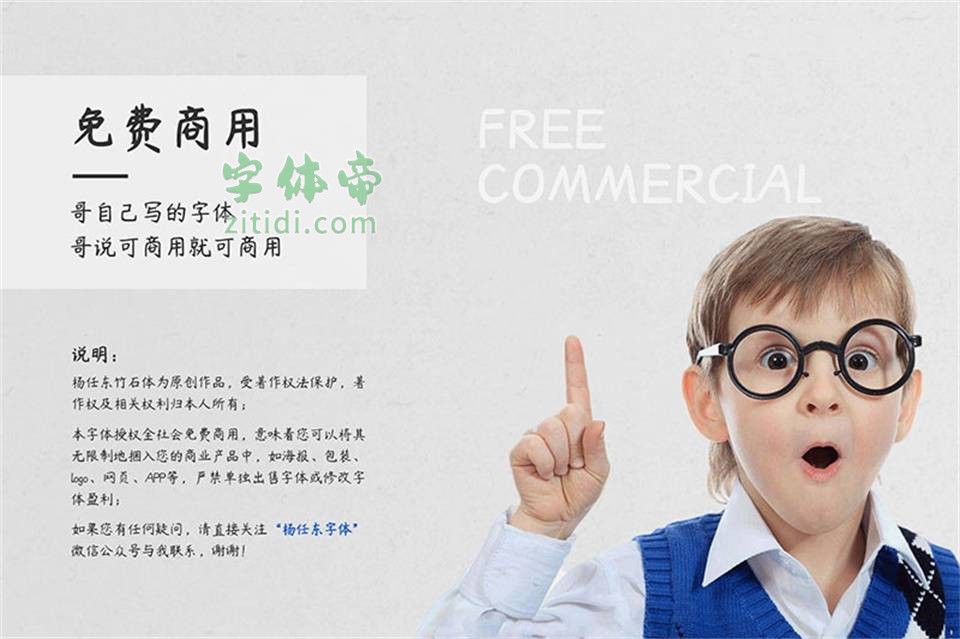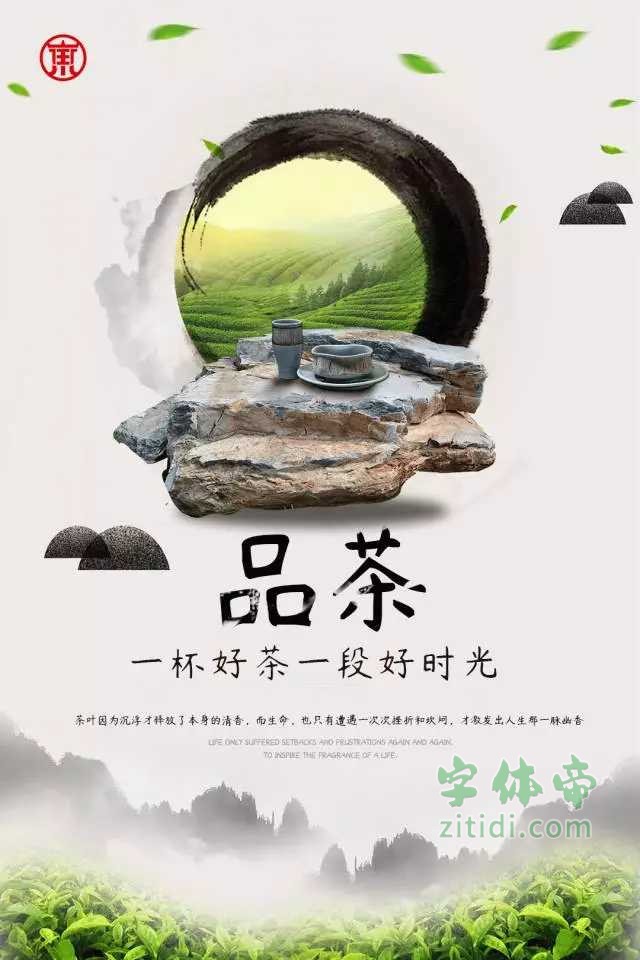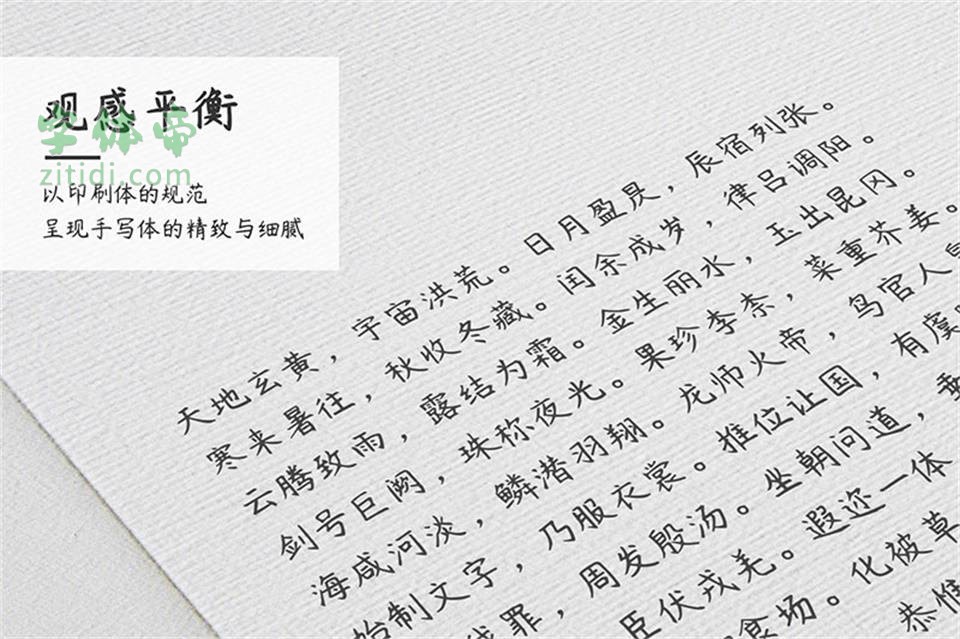
拿字体版权问题来说,形势可谓十分严峻。高额的字体授权费用和许多版权归属不明朗的字体始终困扰着设计师。而现实情况是免费可商用的字体少之又少,字体盗版情况屡禁不止。那么字体还能不能好好用了?答案当然是:能!全球首款七字重中文手写字体,杨任东竹石体正式发布!重点是,免费可商用!!!
杨任东竹石体按照GB2312-80书写,并增补了少量常见汉字,单个ttf格式字体文件包括7311个字符,涵盖了日常生活用字99.8%的需求;整套字体有7个字重,也就是共有7个ttf格式字体文件,全套字体共计50000余个字符。
本套字体的部分文字还存在重心不一致、细节瑕疵等问题,不过作为手写体并不影响使用,作者将在后续版本中不断改进。如果您有任何意见或者建议,请直接关注“杨任东字体”微信公众号与我联系,敬请您的持续关注,期待您的宝贵意见,谢谢!
“杨任东竹石体-Bold”是一款书写很新颖的字体,字体大方,适合各种设计作品使用!欢迎下载!